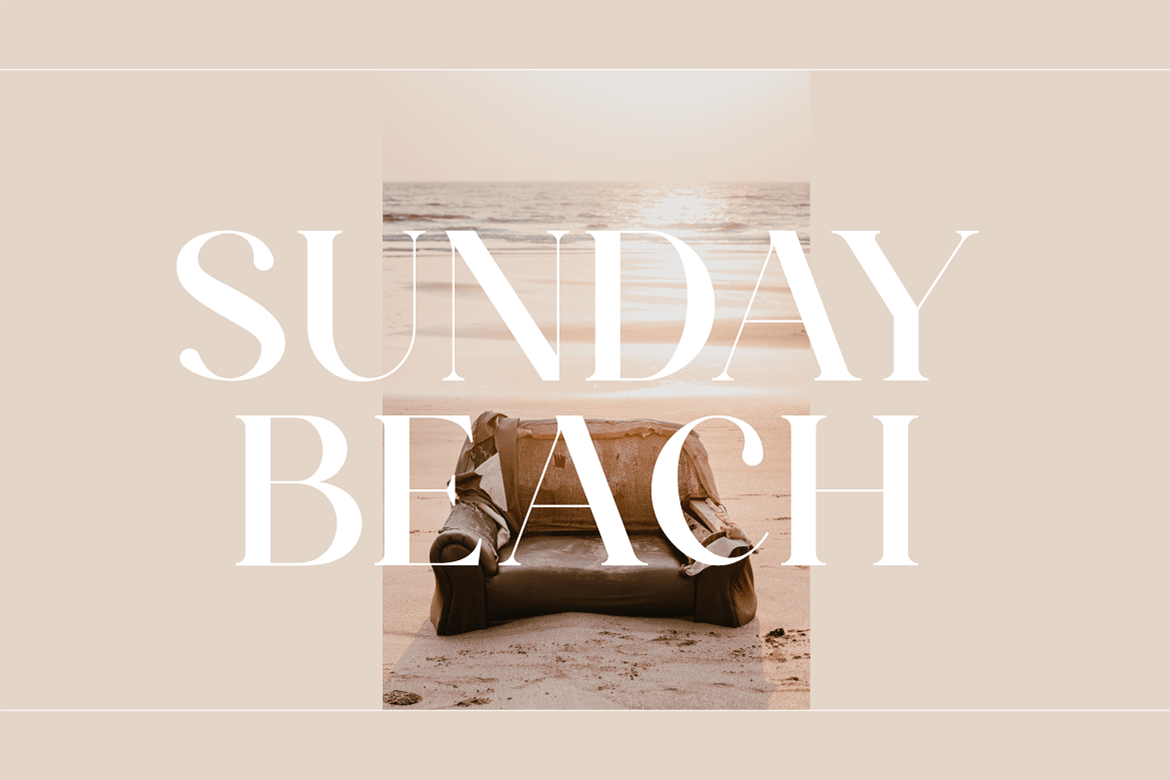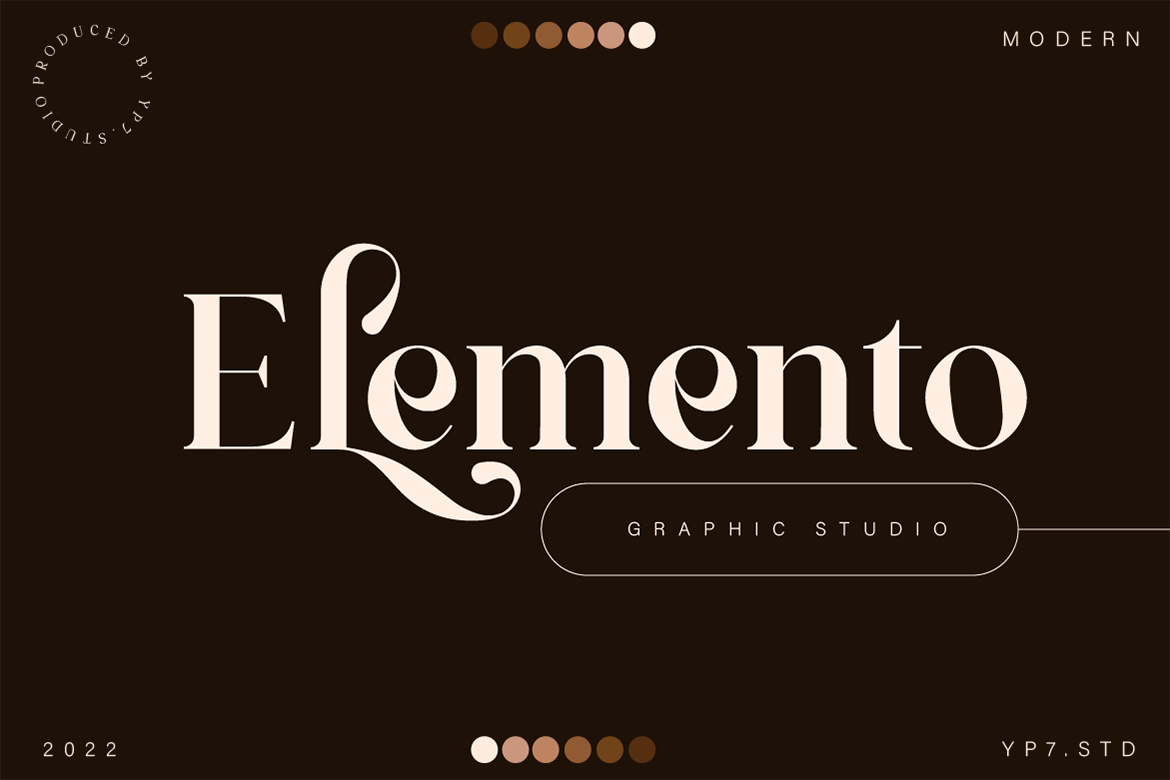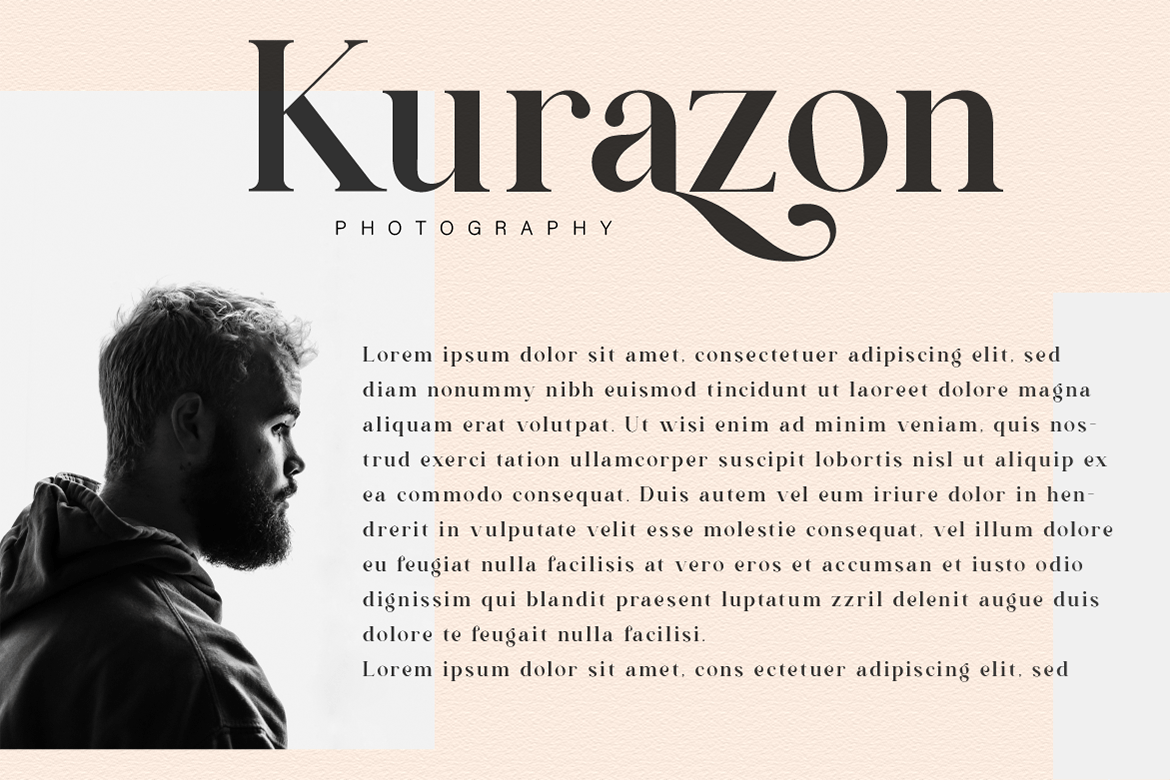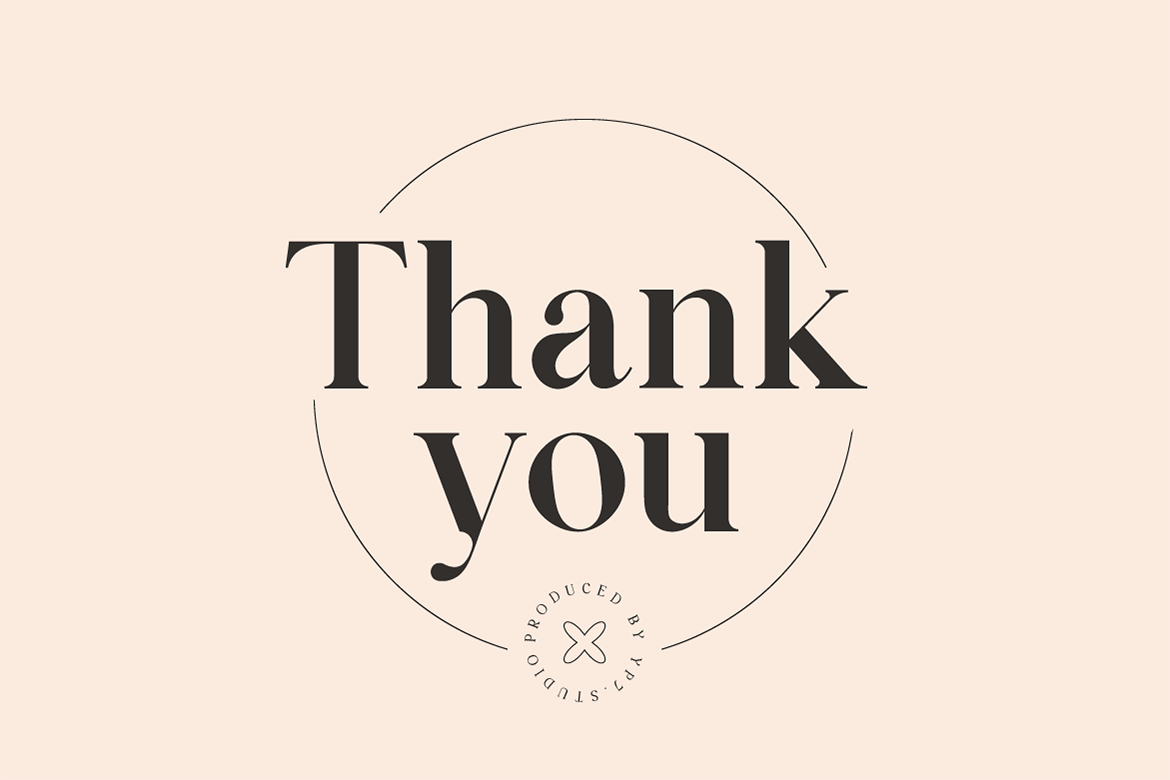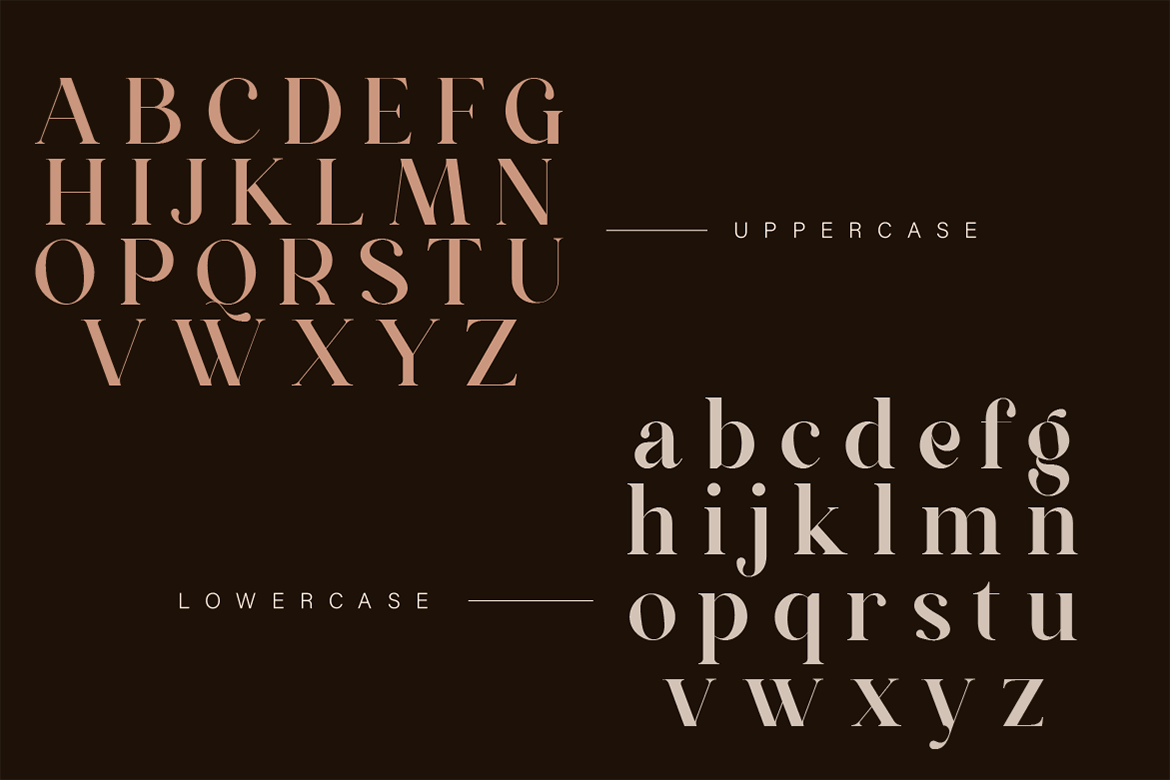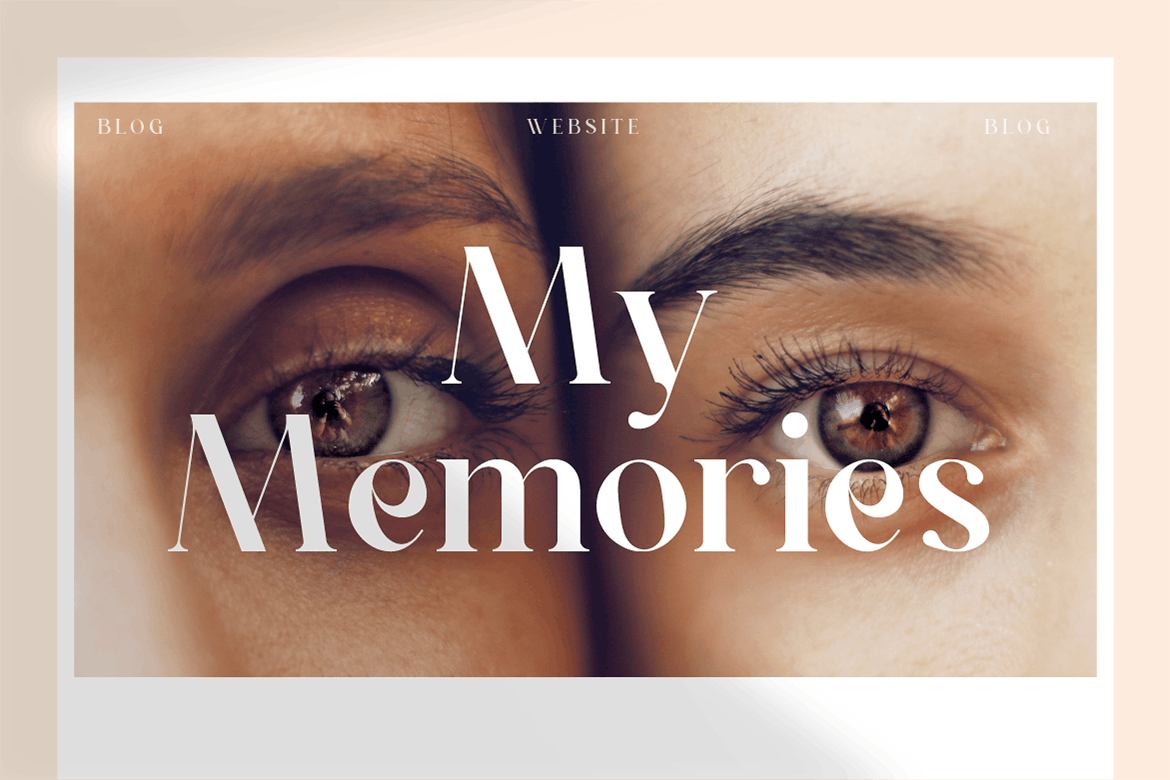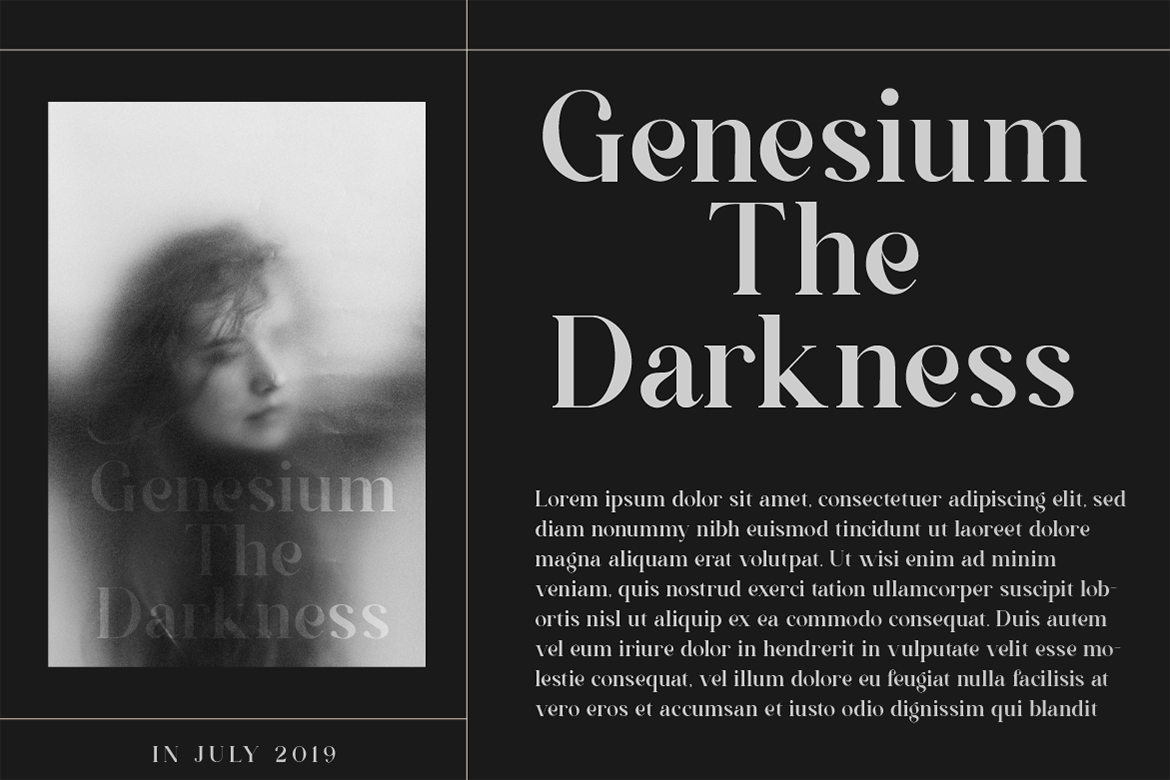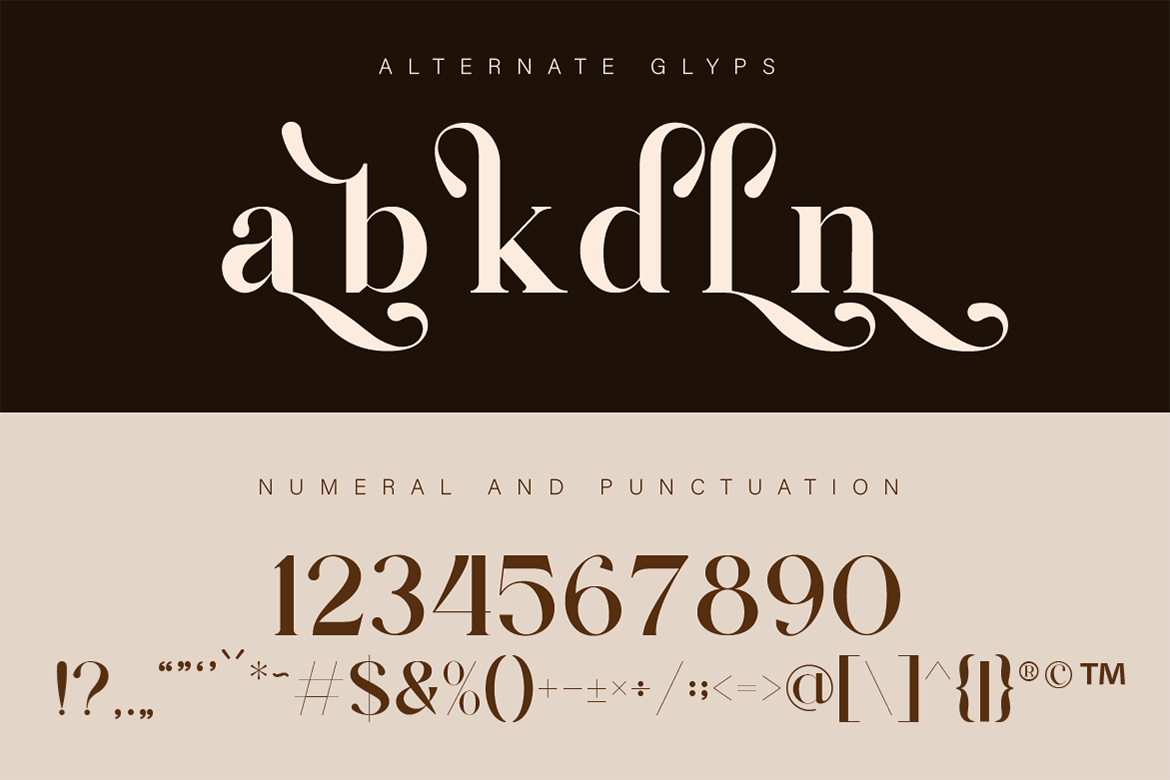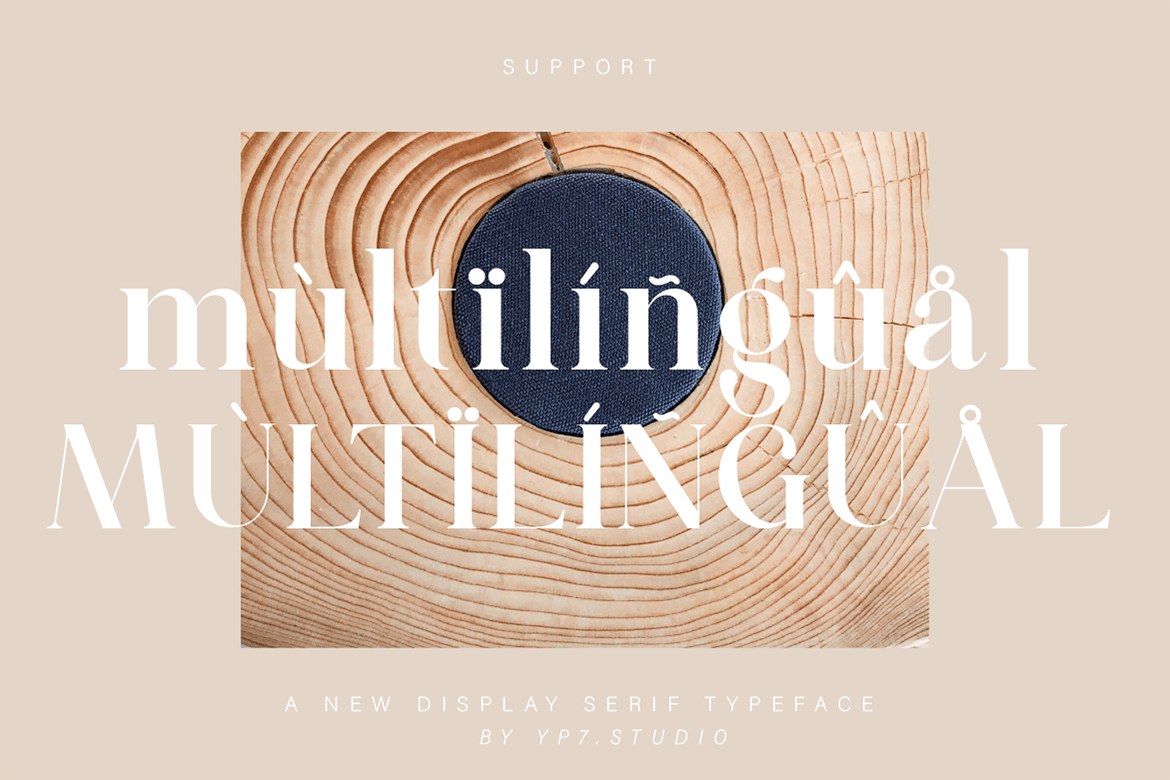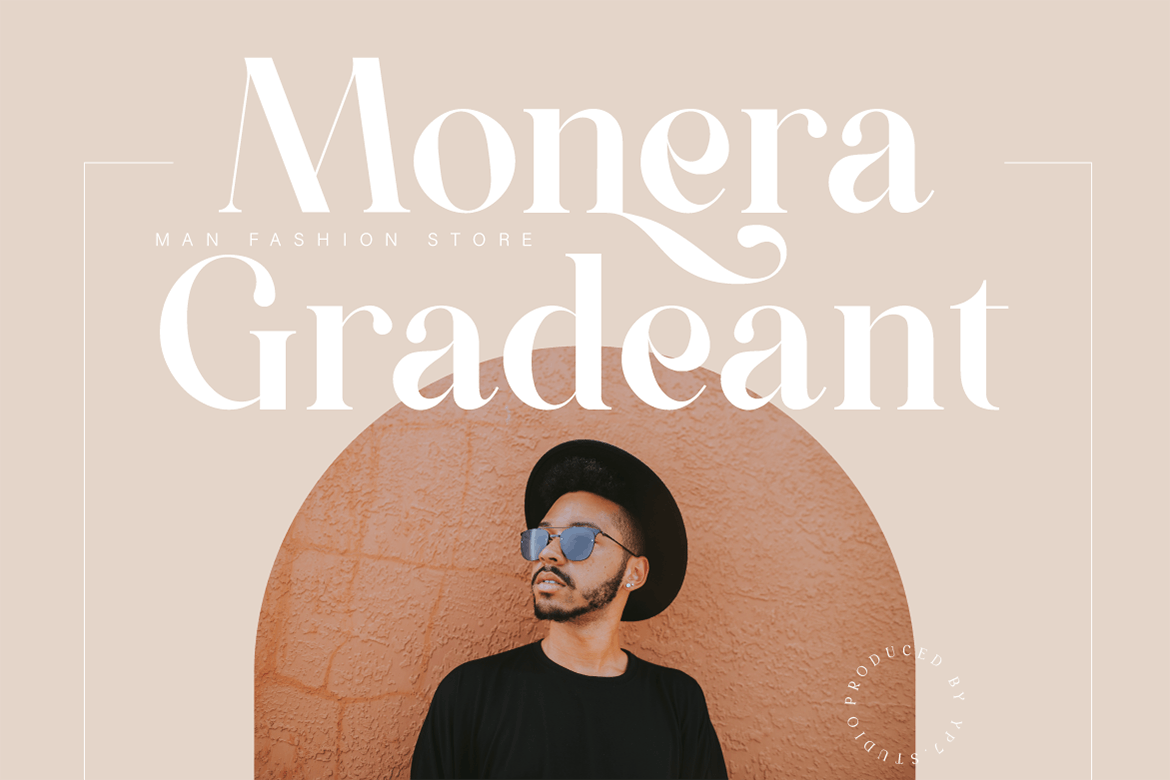
Modern Luxury Serif Font
فونت سریف لوکس و مدرن Monesta برای طراحی‌های خاص و خلاقانه.
فونت سریف لوکس و مدرن Monesta یک انتخاب عالی برای طراحان است که به دنبال ظاهری شیک و حرفه‌ای هستند. این فونت با طراحی خاص خود می‌تواند به پروژه‌های مختلف زیبایی و جذابیت بیشتری ببخشد.
• حروف بزرگ
• حروف کوچک
• اعداد و نشانه‌گذاری